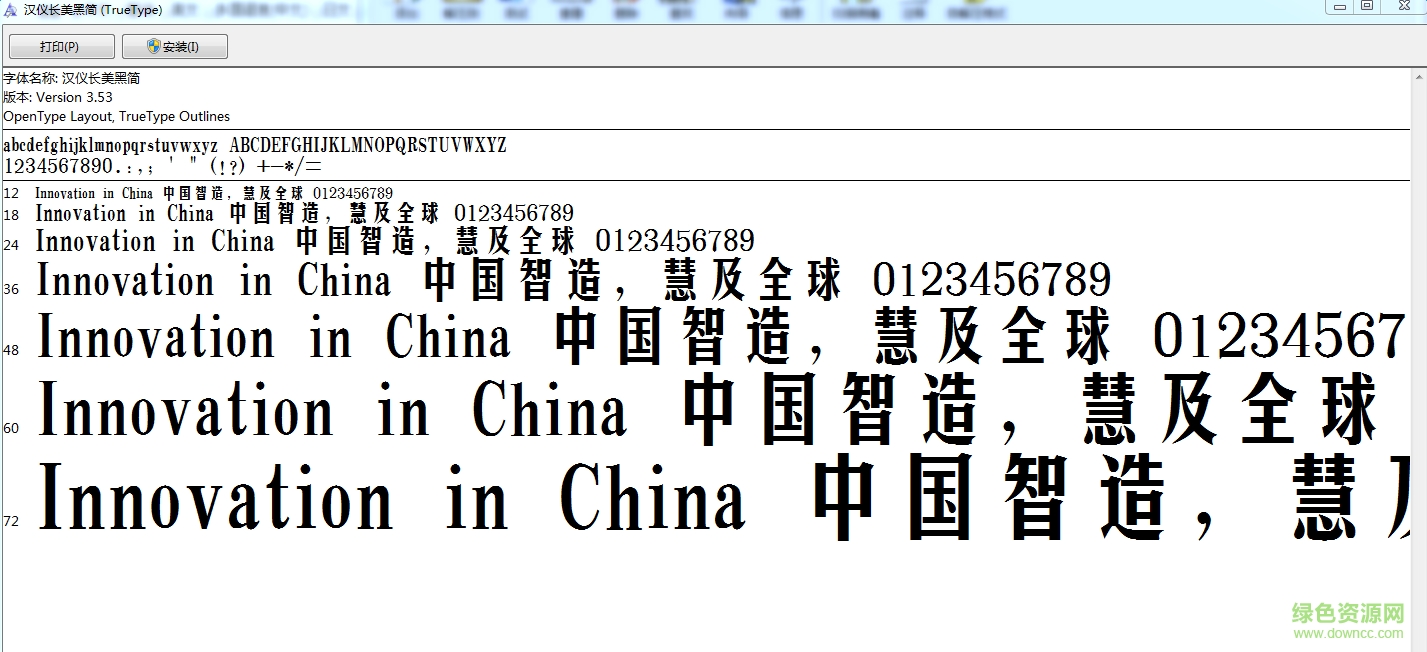
漢儀長(zhǎng)美黑簡(jiǎn)字體是一款漢儀類(lèi)豎長(zhǎng)簡(jiǎn)體字體軟件,長(zhǎng)美黑簡(jiǎn)體給人非常優(yōu)美文雅的感覺(jué),清新醒目,適用于海報(bào)、廣告等標(biāo)題應(yīng)用,同時(shí)也深受廣大書(shū)法家的喜愛(ài),還有更多好看字體盡情期待,歡迎到綠色資源網(wǎng)下載體驗(yàn)!